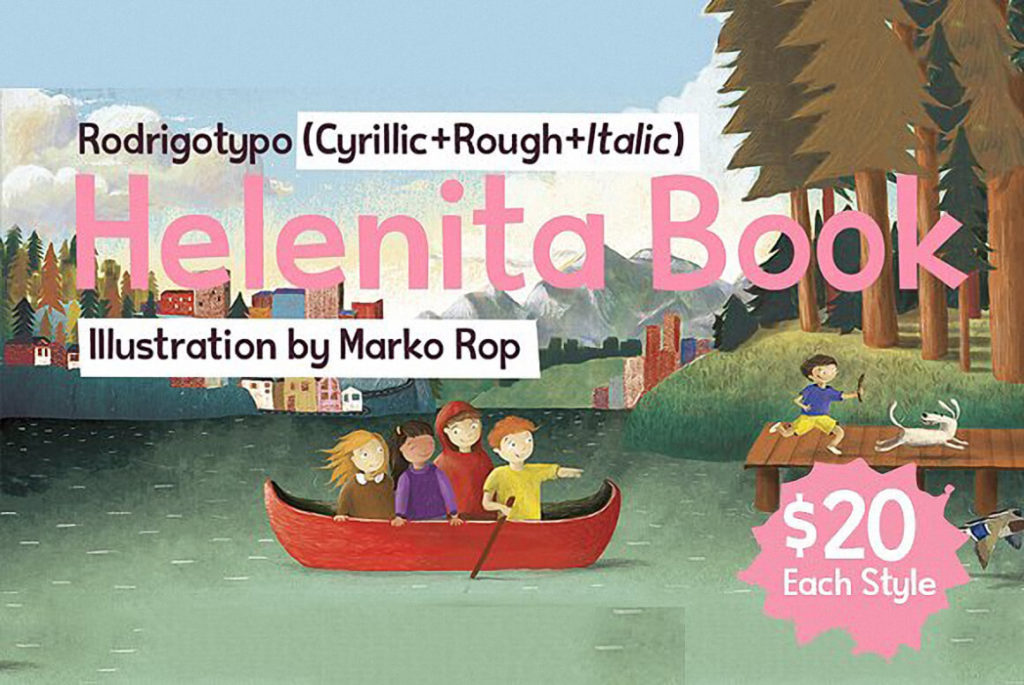
Шрифт Helenita Book — это семейство рисованных (hand-drawn) шрифтов от словолитни Rodrigo Typo, выпущенное в 2014 году. Гарнитура включает четыре стиля, которые имитируют различные текстуры и «ручные» эффекты: Rough, Italic, Rough Italic и базовый. Шрифт отличается жирными, плотными буквами с постоянной шириной штриха и низким контрастом, что придаёт тексту выразительный и современный вид. Поддерживает кириллицу, что делает его отличным выбором для проектов на русском языке, где нужна неформальная и художественная типографика. Если вы ищете яркий шрифт с характером для креативных задач, вы можете ознакомиться с ним на этой странице.